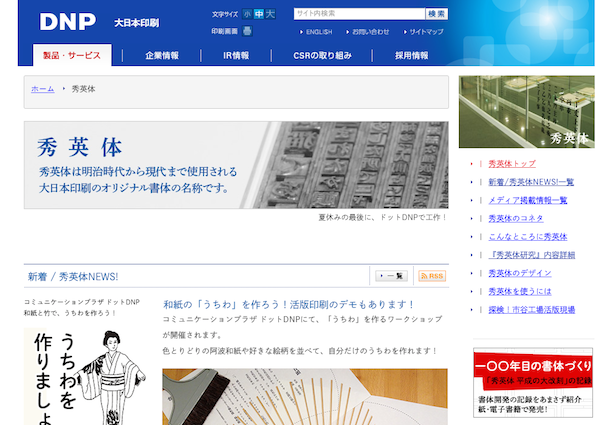
■どのようなサイトですか?
大日本印刷(DNP)のオリジナル書体である「秀英体」の公式サイトです。
書体見本や最新の提供事例、イベント情報、そして秀英体に関するちょっとした出来事や話など、いろいろな秀英体の情報をお届けしています。
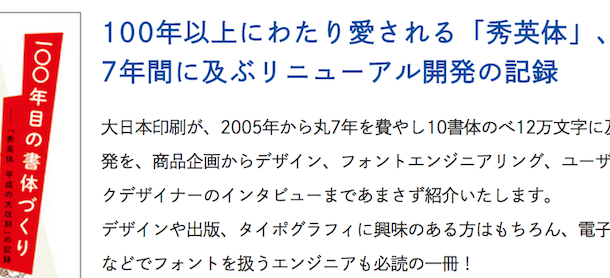
■TypeSquareを導入された背景を教えてください。
書体を見てもらうことが、その書体を知ってもらう近道です。
まずは「秀英体」をみんなの目に届くところで積極的に使おう。みんなが気付いてくれて、興味を持ってもらえれば嬉しいなあ。そんな思いから公式サイトでの表示をすべて秀英体フォントにしました。
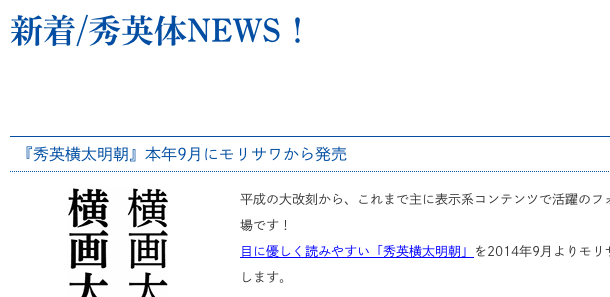
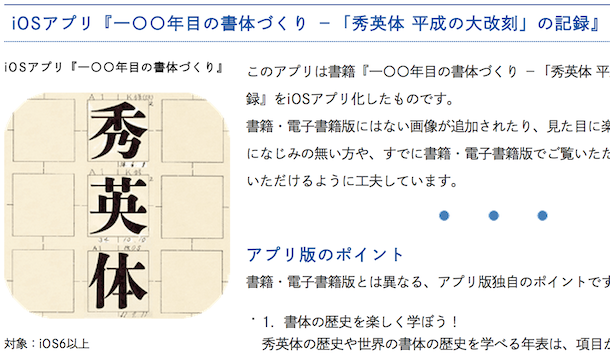
これまでもタイトルや見出しに画像化した「秀英明朝」を使っていましたが、サイトを見る環境によっては文字の縁がぼやけたり、文字の線がギザギザに見えることがありました。
しかし、TypeSquareでは画像化が不要になり、フォントで表示されるので、表示機器や文字サイズにかかわらず、綺麗に表示することができるようになりました。また本文には、Webサイトでの美しさと読みやすさを演出する「秀英角ゴシック銀」を選びました。